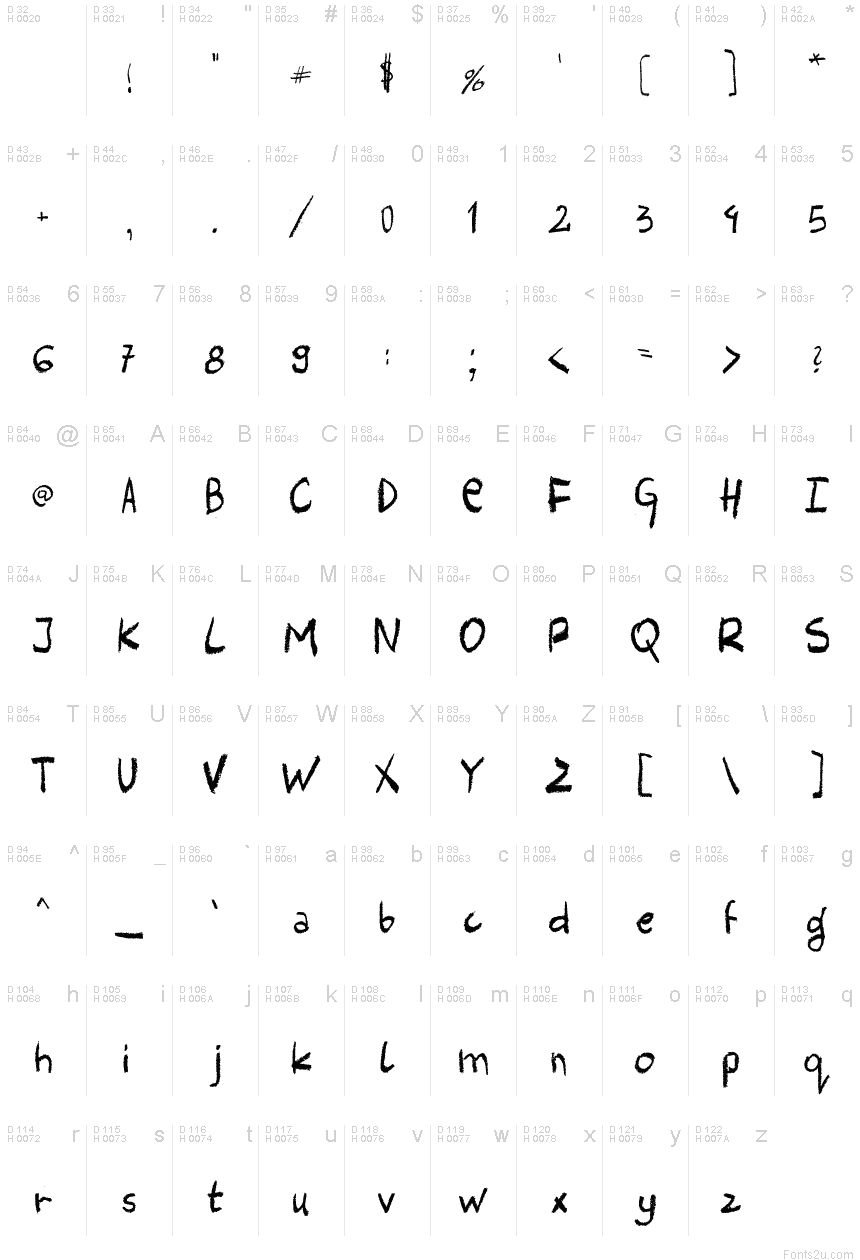
Harlem Clown autorstwa Leszeka Soltysa to darmowy, surowy krój pisma typu brush script o autentycznym, ręcznie malowanym charakterze. Litery wyglądają, jakby zostały szybko naniesione na ścianę – z poszarpanymi krawędziami, nierównym naciskiem i dynamicznymi łączeniami, co nadaje całości luźny, zabawny i nieco niepokorny wyraz.
Świetnie sprawdza się na plakatach, ulotkach imprezowych, grafikach muzycznych, projektach streetwearowych i okładkach zinów, gdzie ta „brudna”, malarska energia odgrywa główną rolę. Jako darmowy font, nadaje się również do krótkich nagłówków, tytułów i wyeksponowanych cytatów, ponieważ tekstura pędzla wysuwa się na pierwszy plan i nadaje nawet krótkim słowom żywy, nietuzinkowy rytm.
Harlem Clown